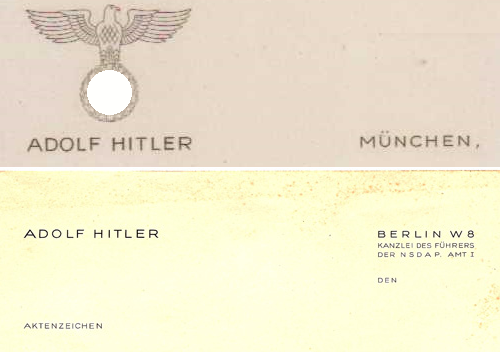
Schriftart Briefkopf Hitler
ich hab ein bisschen gestöbert und den thread über die briefbögen gelesen und den von hitler gefunden. jetzt meine frage, welche schriftart ist das? (der name und »münchen, den«)?
wird wohl irgendeine gothic aus den 20ern sein, davon gibts heutzutage massig
die Auflösung ist eigentlich zu gering um die Schrift genau zu identifizieren. Ich würde als eine mögliche Schrift die Erbar Grotesk Stumpf anbieten. Das Stumpf ist wichtig, es bedeutet einen alternativen Schnitt für das große M. (Das normale M der Erbar ist ähnlich der Futura.)
Die Erbar Grotesk ist aus den frühen 1920ern und könnte zeitlich passen. Eine weitere mögliche Lösung ist die Drescher Grotesk (1930):
Das gibt schon die ungefähre Richtung vor, aber weiteres kann IMHO erst nach der Vorlage eines besseren Scans ausgesagt werden.
Der untere scheint mir dem von Albert Einstein recht ähnlich. Die Frage zu dessen Schrift gab es neulich hier schon mal (hier der Brief noch mal größer und mit Text).
Ich denke, es könnte Aurora Grotesk von Weber sein (oder Saturn, Favourit Grotesk, Elite Grotesk, Edle Grotesk oder andere identische Schriften). (Die alle haben ihre Matrizen von Ludwig Wagner bezogen.) Zwei weiter unten auf dem Briefbogen-Blog kommt der Führer auch noch mal ein bisschen marzialischer.
das beim Albert Einstein die Aurora zum einsatz kommt würde ich auch sagen, allerdings passt die Aurora nicht zum Adolf. bei dem einem ist das R und das M anders, bei dem anderen wirkt das A sehr spitz, das kann aber auch täuschen, dass C wirkt allerdings auch offener als bei der aurora.
Der untere scheint mir dem von Albert Einstein recht ähnlich. Die Frage zu dessen Schrift gab es neulich hier schon mal (hier der Brief noch mal größer und mit Text).
Ich denke, es könnte Aurora Grotesk von Weber sein
(oder Saturn, Favourit Grotesk,
Favourit Grotesk ist doch Dekokacke? Oder gibt es da eine andere Schrift mit dem Namen?
Elite Grotesk, Edle Grotesk
oder andere identische Schriften). (Die alle haben ihre Matrizen von Ludwig Wagner bezogen.) Zwei weiter unten auf dem Briefbogen-Blog kommt der Führer auch noch mal ein bisschen marzialischer.
Auch noch aus der Sippe ist die Splendid Grotesk:
Tja, das sind alte Bleisatzschriften die dann auch von Giesserei zu Giesserei anders ausfielen. Schon daher sehe ich schwarz für eine genaue Identifikation. Oder kann jemand mit dem Setzer von Hitlers alten Briefbögen Kontakt aufnehmen? Gibt es hier auch noch Spiritisten?
Kleiner Gedanken am Rande: Die Interstate hat auch tiefe Wurzeln in dieser Ecke. Die freien Schnitte der Blue Highway könnten vielleicht für einfache Parodien brauchbar sein?
Ah ja, da hast Du Recht mit dem M, Robert, aber Interstate sehe ich hier irgendwie gar nicht.
das mit der Interstate war nur eine vorschlagende Randbemerkung für billige Parodien. Ich habe da an den freien Schnitt DType (nur Großbuchstaben) gedacht. Das wäre schnell und einfach zu machen.
Mir erscheint bei beiden Briefköpfen das A am Wortanfang zu klein und irgendwie unpassend zum Rest des Names. Schlechter Scan? Ist das A vielleicht in beiden Originalen spitz? Ansonsten ist auch das R irgendwie nicht besonders hybsch und der Bogen in beiden Scans IMHO unvollständig. Die Scans sind zu schlecht für eine ganz sichere Indentifikation.